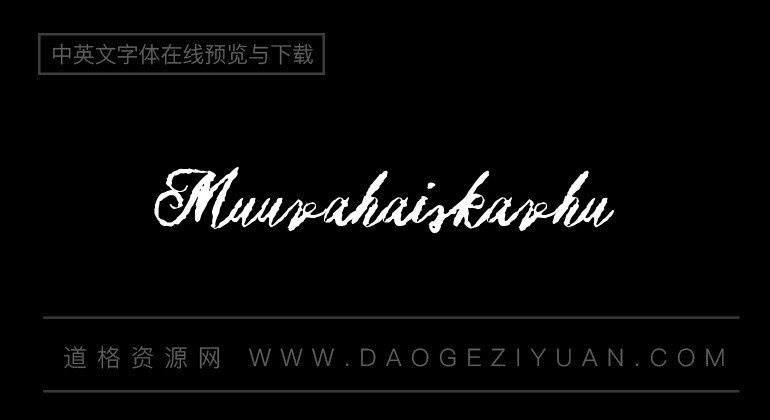
? Muurahaiskarhu 字体是一款欧洲风格的英文字体,它采用了精致的细节和自然的曲线,可以让文字看起来更加优雅,舒适。Muurahaiskarhu 字体拥有非常丰富的符号,可以用来创建多种不同的文本效果,它也支持多种语言,可以用于欧洲文字和其他语言的排版。内容介绍
Muurahaiskarhu是一款非常不错的手写艺术字体,具有很好的视觉感,适合于文化类的宣传设计、商业类品牌的广告和产品包装设计以及个性化文字排版等较多场景。